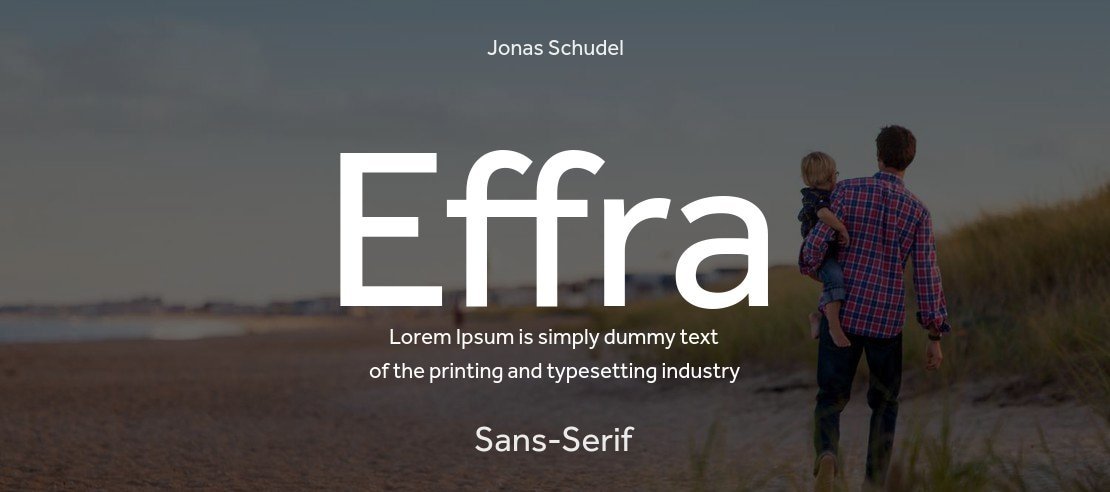
Di era digital, branding usaha bukan lagi sekadar logo. Salah satu elemen terpenting yang sering luput adalah pemilihan font. Font sans serif modern kini jadi favorit banyak brand karena tampilannya yang bersih, minimalis, dan profesional.
Data Design Trends Report 2024 menyebutkan bahwa 70% perusahaan baru memilih font sans serif sebagai identitas utama mereka karena dianggap relevan dengan gaya desain modern dan mudah diadaptasi ke berbagai media — baik digital maupun cetak.
Font sans serif modern adalah bahasa visual baru dalam branding. Bersih, tegas, dan profesional—membuat setiap brand lebih mudah dipercaya.” – Rhino Indonesia
Kenapa Memilih Font Sans Serif untuk Branding?
- Minimalis dan modern → memberi kesan profesional.
- Mudah dibaca → baik di layar kecil maupun cetak besar.
- Fleksibel → cocok dipakai di logo, kemasan, hingga desain sablon kaos.
- Timeless → tetap relevan meski tren berubah.
Tips Menggunakan Font Sans Serif di Branding Usaha
- Gunakan maksimal 2–3 font dalam satu brand guideline.
- Padukan bold untuk headline dengan regular untuk body text.
- Pastikan kontras dengan background agar mudah dibaca.
- Uji di berbagai media: media sosial, kemasan, merchandise, hingga website.
21 Font Sans Serif Modern untuk Branding Usaha
1. Gilroy
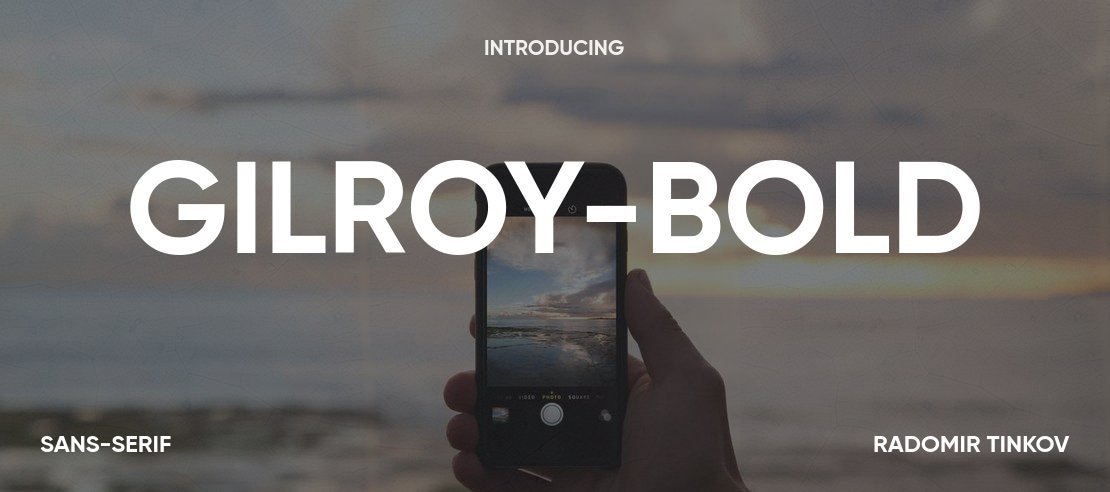
- Karakteristik: Geometris, simple, modern.
- Kelebihan: Cocok untuk headline maupun body text.
- Kesan: Minimalis dan profesional.
- Cocok untuk: Logo startup kreatif.
Gilroy adalah salah satu font sans serif populer yang sering dipakai agensi desain. Bentuknya tegas namun tetap enak dibaca, baik untuk logo maupun teks panjang. Font ini mampu menampilkan citra profesional dan modern, sangat ideal untuk brand UMKM kreatif yang ingin tampil lebih premium.
2. Circular Std
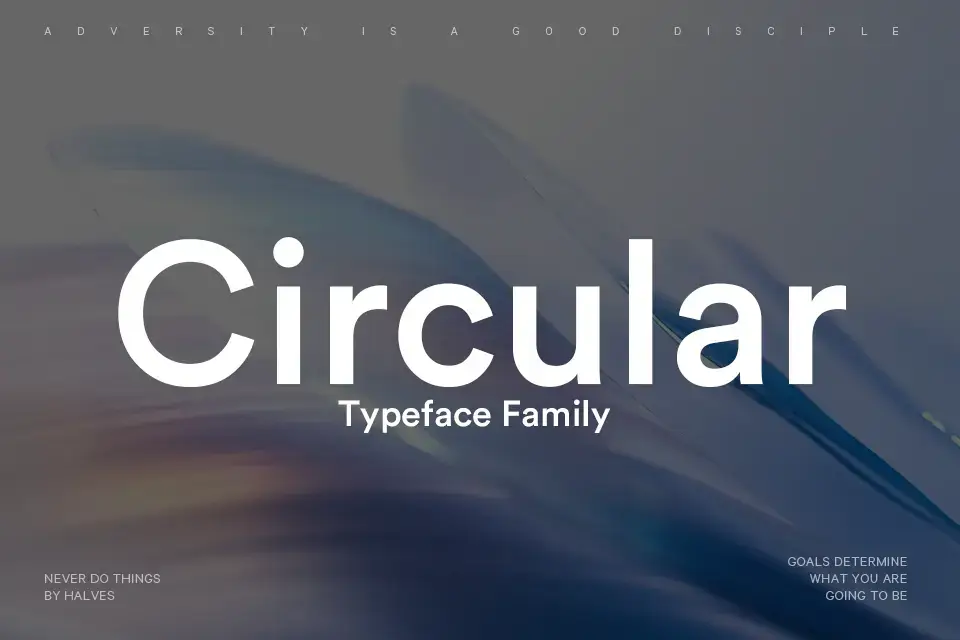
- Karakteristik: Bulat, ramah, modern.
- Kelebihan: Membawa nuansa hangat pada brand.
- Kesan: Friendly dan approachable.
- Cocok untuk: Brand lifestyle & retail.
Circular Std terkenal dengan karakter bulat sempurnanya. Font ini memberikan kesan ramah dan hangat tanpa mengurangi profesionalisme. Banyak brand retail dan lifestyle menggunakannya untuk menampilkan keakraban kepada pelanggan sekaligus mempertahankan estetika modern.
3. Inter
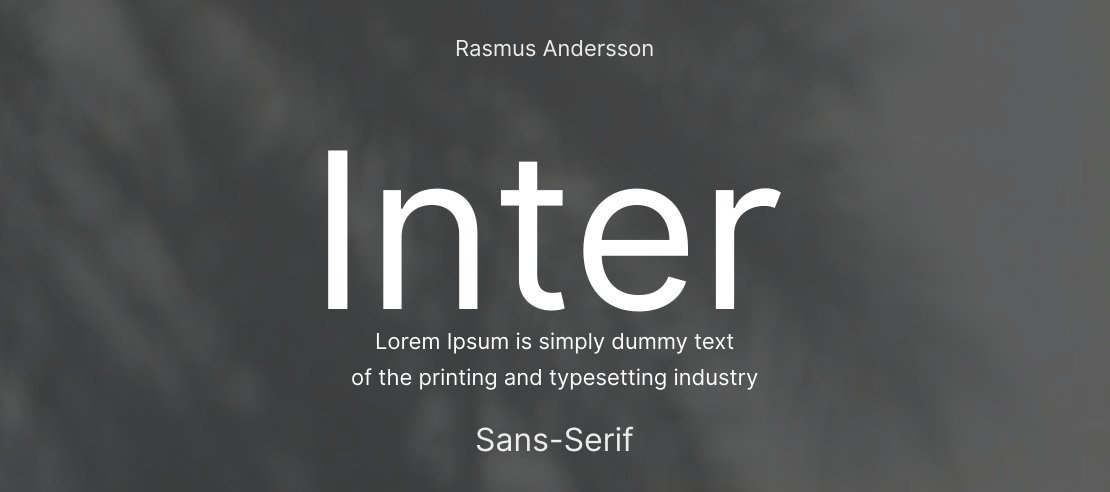
- Karakteristik: Desain khusus untuk layar.
- Kelebihan: Super readable di web & mobile.
- Kesan: Serius dan modern.
- Cocok untuk: Website dan aplikasi.
Inter dirancang untuk dunia digital. Teks terlihat jernih bahkan di layar kecil, membuatnya cocok untuk aplikasi dan website. Dengan kesan modern dan profesional, Inter menjadi pilihan tepat untuk brand yang ingin fokus pada user experience di dunia online.
4. SF Pro Display (Apple)
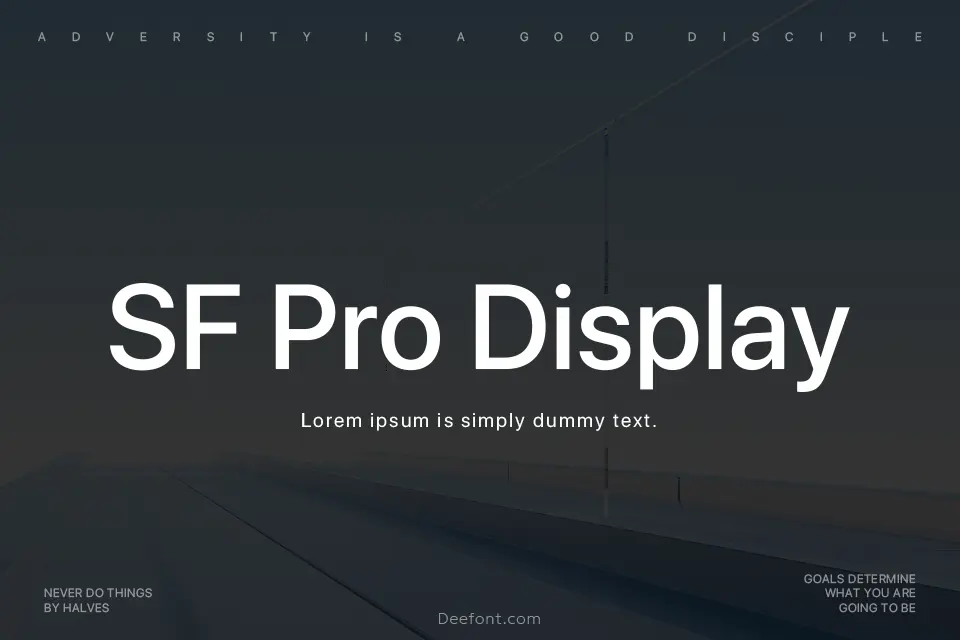
- Karakteristik: Bersih, premium, teknologis.
- Kelebihan: Ikonik karena dipakai Apple.
- Kesan: Futuristik, modern, high-class.
- Cocok untuk: Brand teknologi.
SF Pro Display digunakan Apple di semua produknya, mulai dari iPhone hingga Mac. Hal ini membuat font ini identik dengan kualitas tinggi dan eksklusif. Brand yang menggunakan SF Pro Display akan mendapat kesan premium dan modern.
5. Aperçu
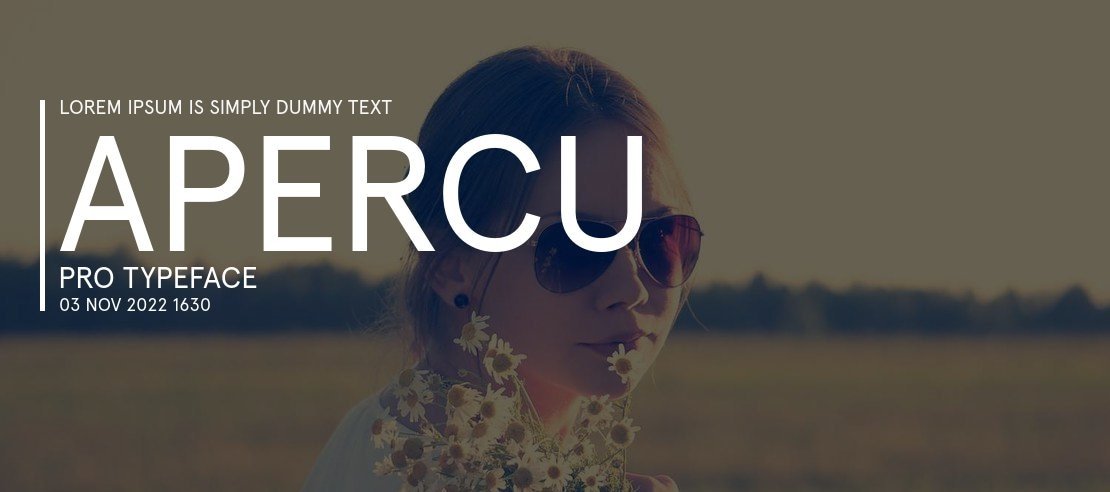
- Karakteristik: Grotesk modern, seimbang.
- Kelebihan: Stylish tanpa mengorbankan keterbacaan.
- Kesan: Trendy dan profesional.
- Cocok untuk: Desain editorial & branding premium.
Aperçu sering dipakai di desain editorial dan majalah modern. Font ini terlihat simple, stylish, dan tetap readable. Cocok untuk brand yang ingin terlihat kekinian tanpa mengorbankan kesan profesional.
6. TT Norms Pro
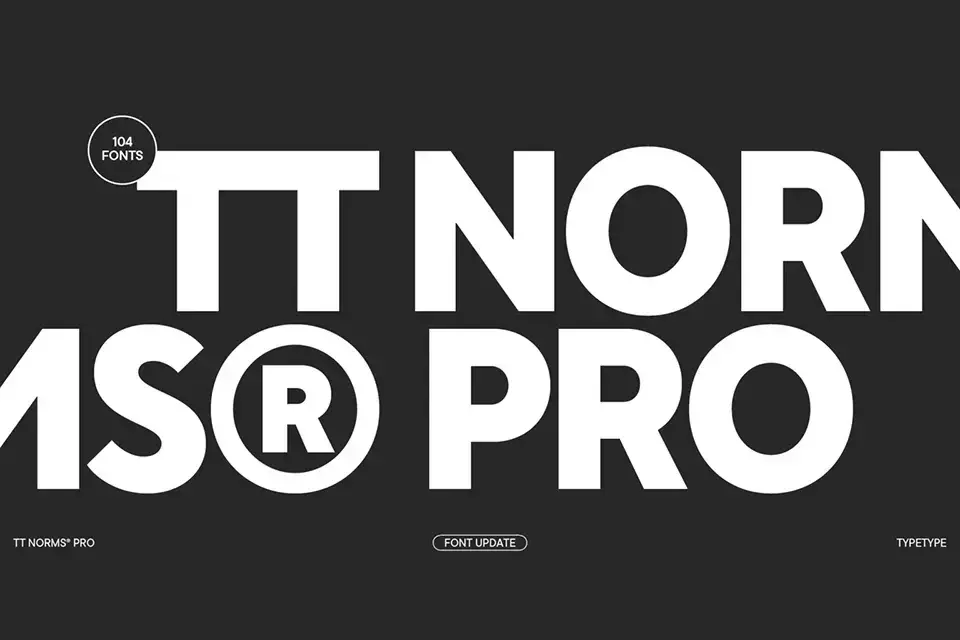
- Karakteristik: Geometris humanist.
- Kelebihan: Banyak variasi weight.
- Kesan: Corporate dan fleksibel.
- Cocok untuk: Branding korporasi besar.
TT Norms Pro menawarkan banyak pilihan ketebalan sehingga sangat fleksibel dipakai untuk berbagai kebutuhan. Dari headline besar hingga teks kecil, font ini menjaga konsistensi visual brand. Banyak perusahaan besar menggunakannya sebagai identitas korporasi.
7. Sofia Pro
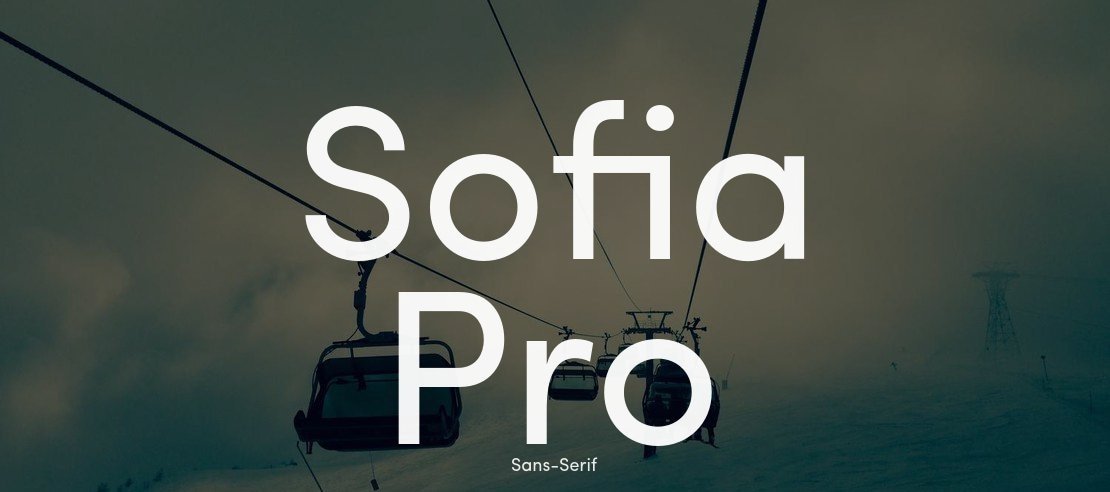
- Karakteristik: Bulat, soft, modern.
- Kelebihan: Ramah tapi tetap elegan.
- Kesan: Friendly, approachable.
- Cocok untuk: Brand makanan sehat & retail.
Sofia Pro menonjol karena bentuk hurufnya yang lembut dan ramah. Cocok untuk produk retail, terutama makanan sehat atau produk anak. Font ini membuat brand terlihat lebih dekat dengan konsumen.
8. Neue Haas Grotesk
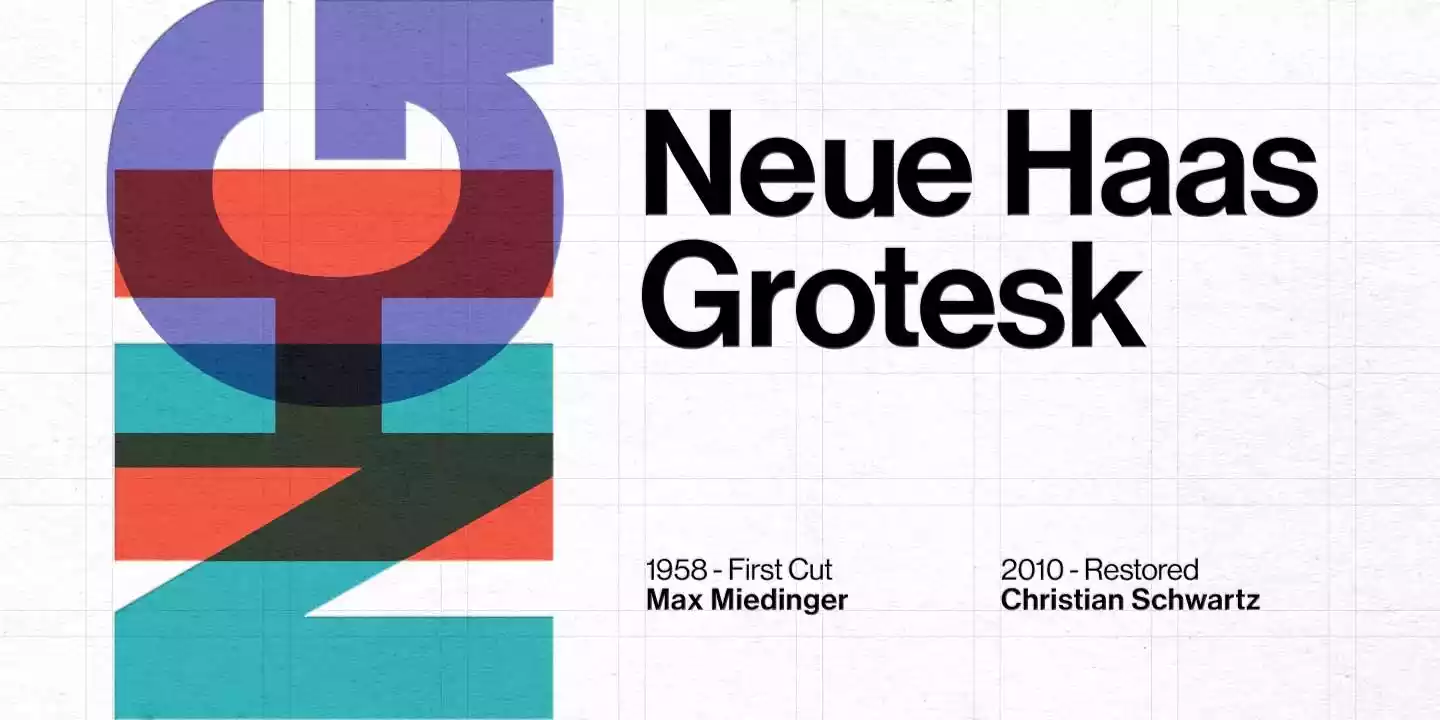
- Karakteristik: Versi asli Helvetica.
- Kelebihan: Ikonik dan timeless.
- Kesan: Corporate, formal, modern.
- Cocok untuk: Branding perusahaan besar.
Neue Haas Grotesk adalah nenek moyang Helvetica. Digunakan sejak lama oleh brand global karena kesan profesional dan modernnya. Brand yang ingin tampil corporate dan serius bisa memanfaatkan font ini.